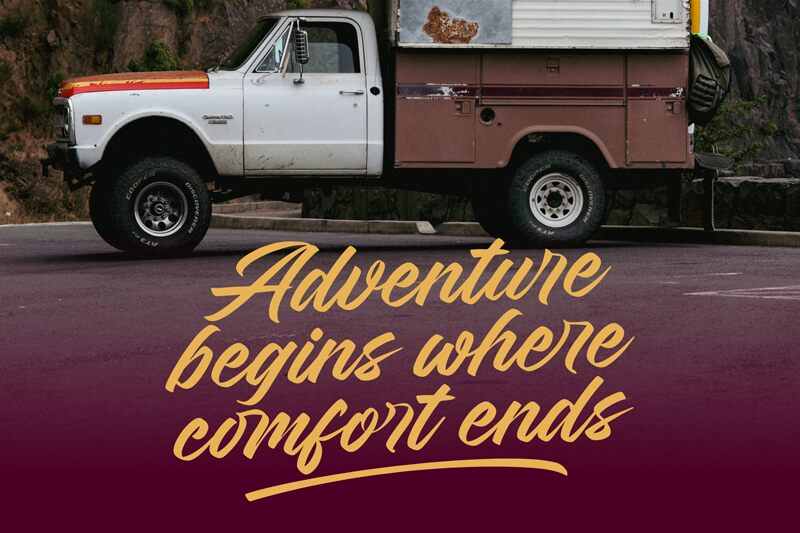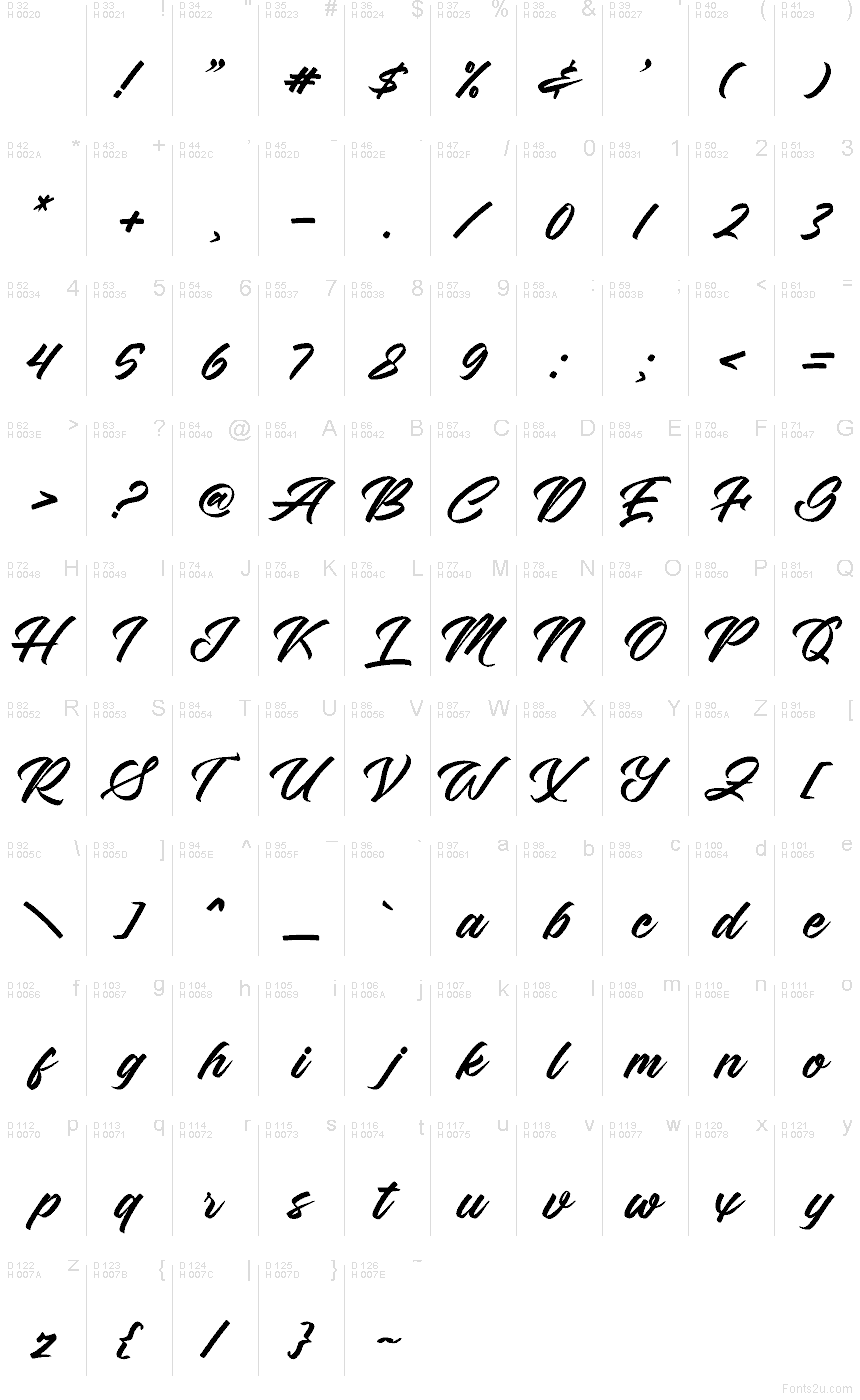
Barty Stones, de ErgibiStd, es una tipografía caligráfica gratuita con un ritmo rápido y de aire artesanal. Las letras se apoyan en trazos amplios y fluidos con remates curvos, otorgando al diseño un aire de firma personal; su trazo grueso le confiere una presencia audaz en lugar de delicada.
Es perfecta para branding, menús de cafeterías, packaging de belleza, portadas de música y títulos en redes sociales donde se busca una fuente gratuita que se sienta personal y llena de movimiento. Úsala para titulares cortos, bocetos de logotipos, monogramas o nombres en invitaciones, especialmente cuando ese trazo inicial pronunciado y la fluidez en la conexión entre letras puedan hacer el trabajo pesado.